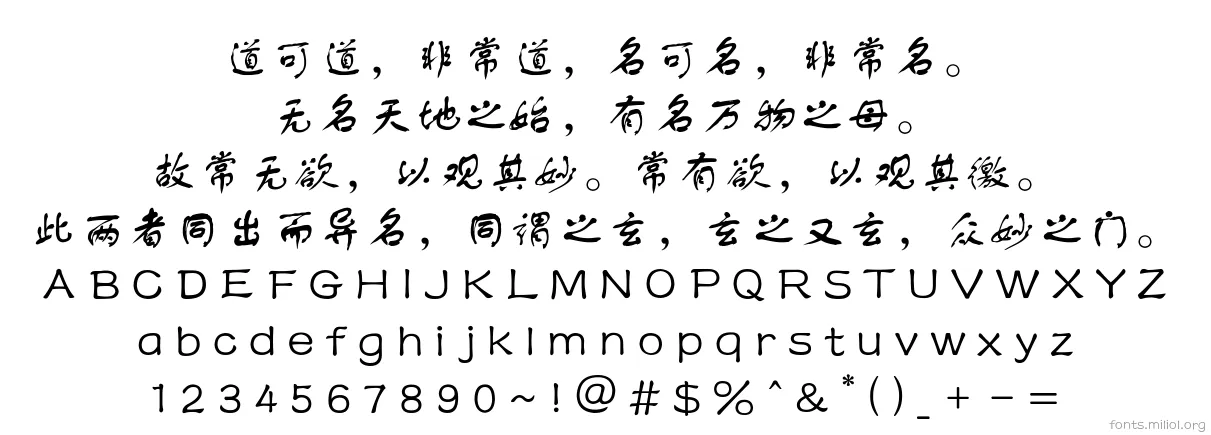
《方正舒体_GBK:传统与现代交融的书法字体》
方正舒体_GBK(FZShuTi-S05)是一款兼具书法韵味与实用性的中文字体,以GBK编码标准设计,覆盖了繁简中文及多种符号,适用于印刷、广告、影视等多领域。其笔画舒展流畅,保留了毛笔书写的自然韵律,同时通过数字化处理确保了屏幕显示的清晰度,完美平衡了艺术性与功能性。
作为方正字库的经典作品,舒体_GBK的优雅风格尤其适合文化类标题、品牌宣传等场景,能为设计增添传统美学气息。其兼容性广泛,支持Windows、macOS等主流系统,满足跨平台使用需求。无论是设计师还是普通用户,都能通过这款字体感受汉字书法的独特魅力。